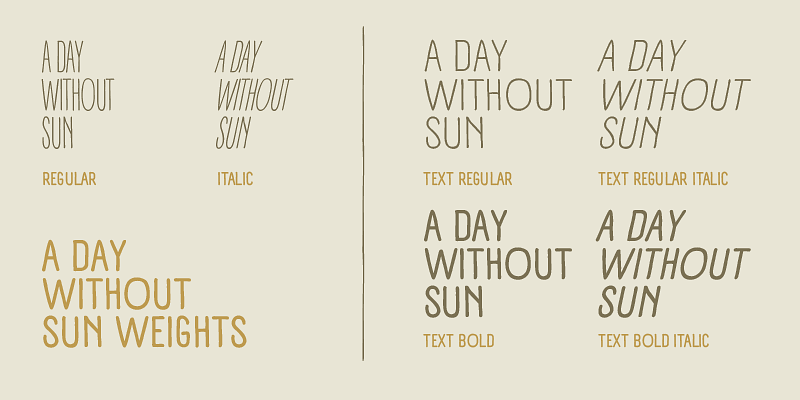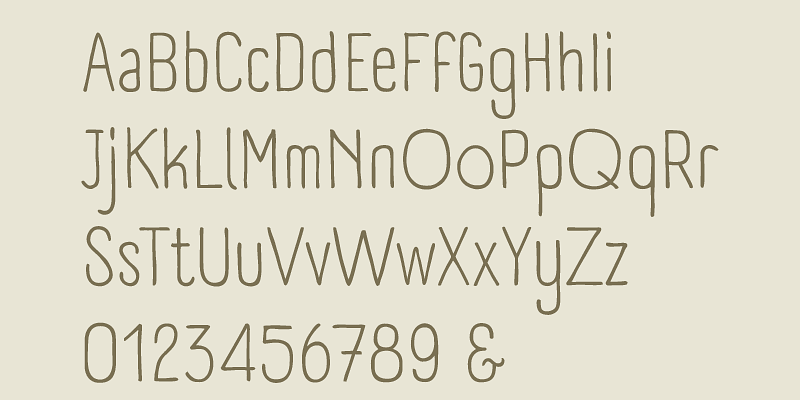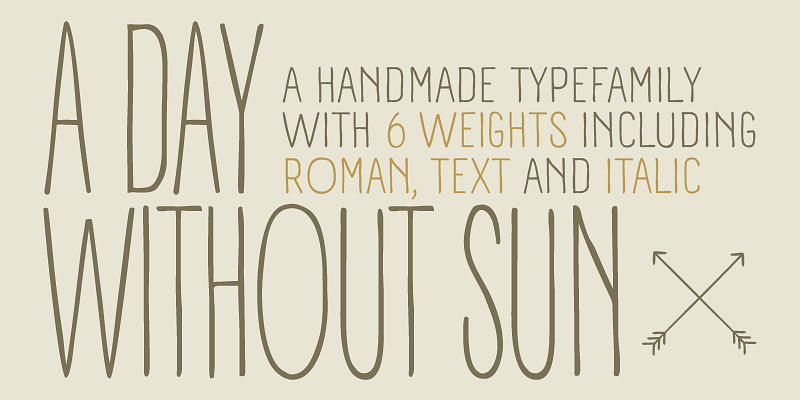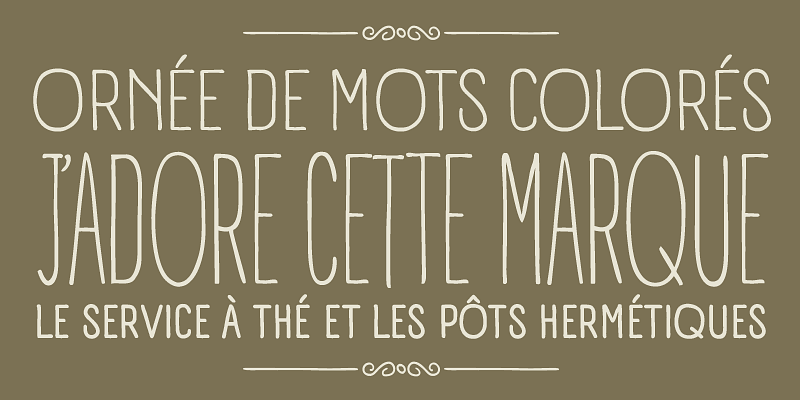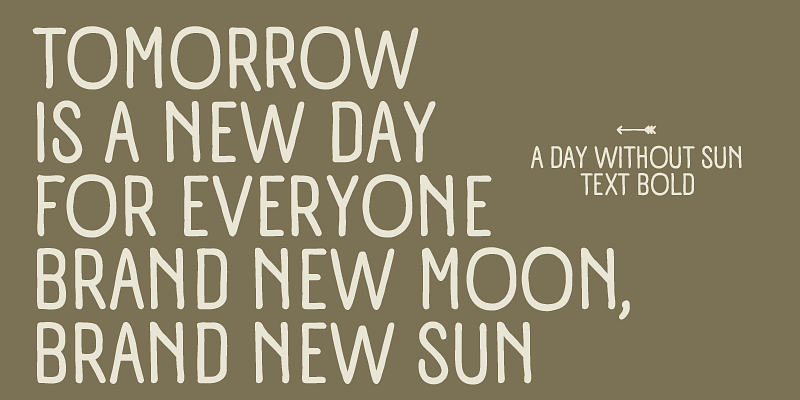
A Day Without Sun은 Cosimo Lorenzo Pancini가 Debora Manetti의 독창적인 디자인을 참고하여 만든 Panforte의 초집약 버전입니다. 쉽고 큰 획의 손글씨로 표현한 이 서체는 빈티지한 손글씨 스타일의 미묘한 우아함과 함께 인조 수작업 방식으로 텍스트를 조판할 수 있는 매우 압축된 서체입니다. 이 서체는 라틴 알파벳을 사용하는 40여 개의 언어를 지원하고 엄선된 발음 구별 부호가 추가되었으며 그리스어 및 키릴 문자도 함께 제공됩니다. 손으로 만든 거친 세부 사항은 중간 및 높은 포인트 크기에서 볼 수 있지만 텍스트로 설정할 때 글꼴 효과에는 영향을 미치지 않습니다. A Day Without Sun OpenType 기능에는 소문자, 구식 숫자 및 고유한 손글씨 형태를 유지하는 데 도움이 되는 합자 세트가 포함됩니다(디자인 소프트웨어에서 “표준 합자” 옵션을 선택 취소하여 끌 수 있음).